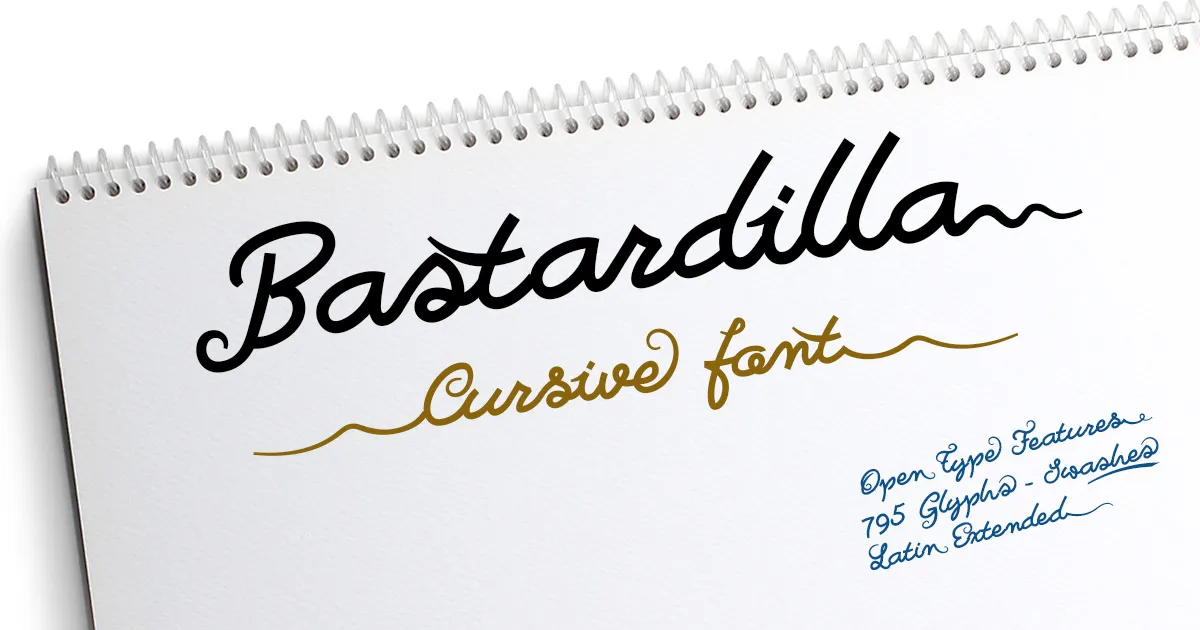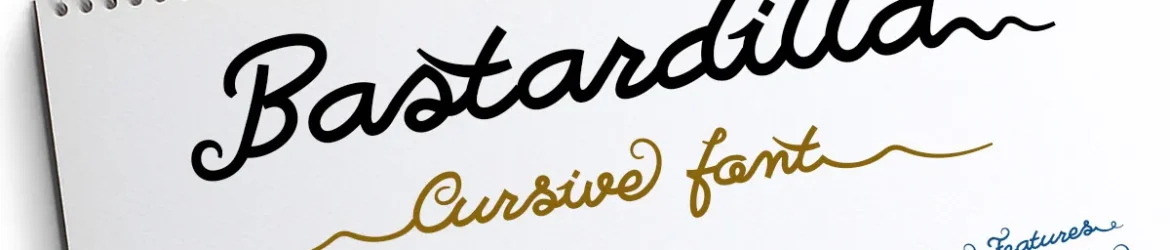
Bastardilla é uma fonte escrita a mão concatenada que apresenta uma vasta gama de letras capitalizadas e minúsculas, além dos elementos especiais necessários para torná-la única e vibrante. No total, o versão comercial contém dois conjuntos completos de letras maiúsculas e três conjuntos de letras minúsculas, incluindo um para letras finais (swashes) e outro para as letras iniciais. Bastardilla é perfeita para criar textos atraentes e personalizados, com seu contraste entre linhas suaves e fortes, proporcionando uma sensação imediata de vida ao texto. Esta fonte foi criada pelo designer defharo e está disponível nas categorias de fontes escrita à mão. Seja você um designer gráfico ou alguém que simplesmente amea a arte da escrita manuscrita, Bastardilla é definitivamente uma fonte que merece ser explorada.